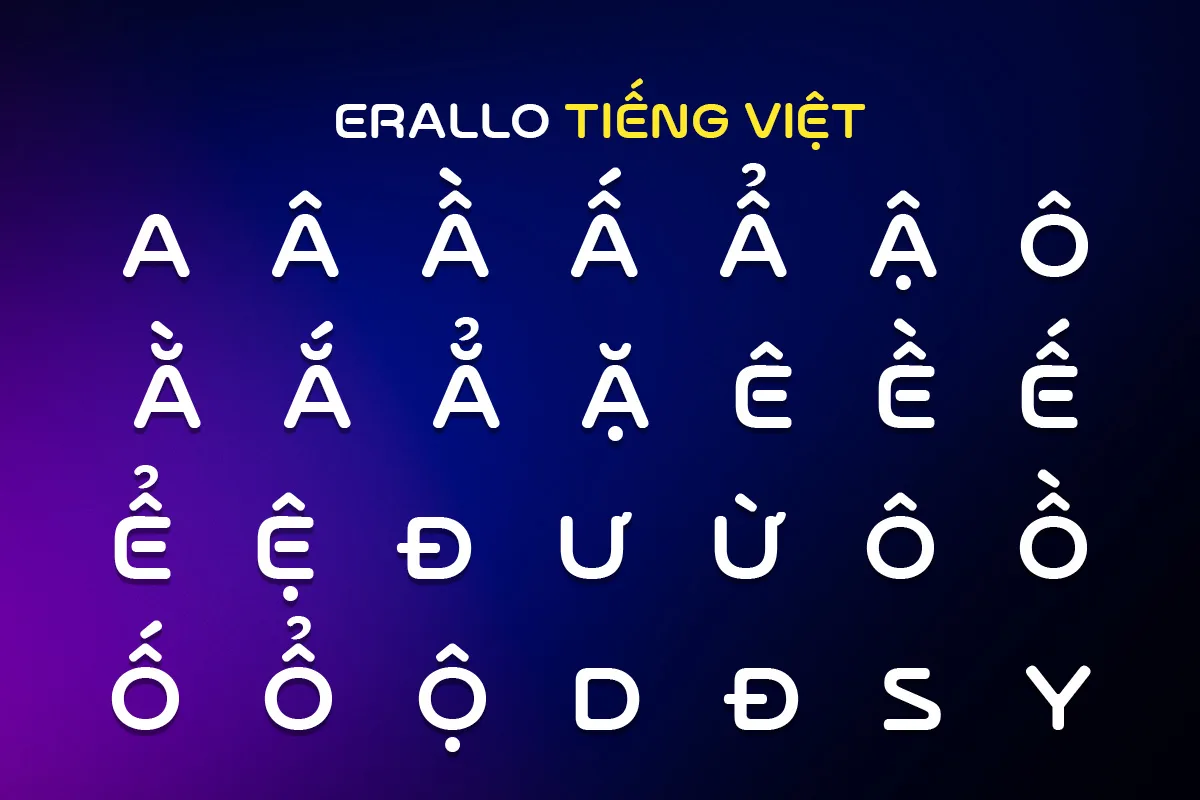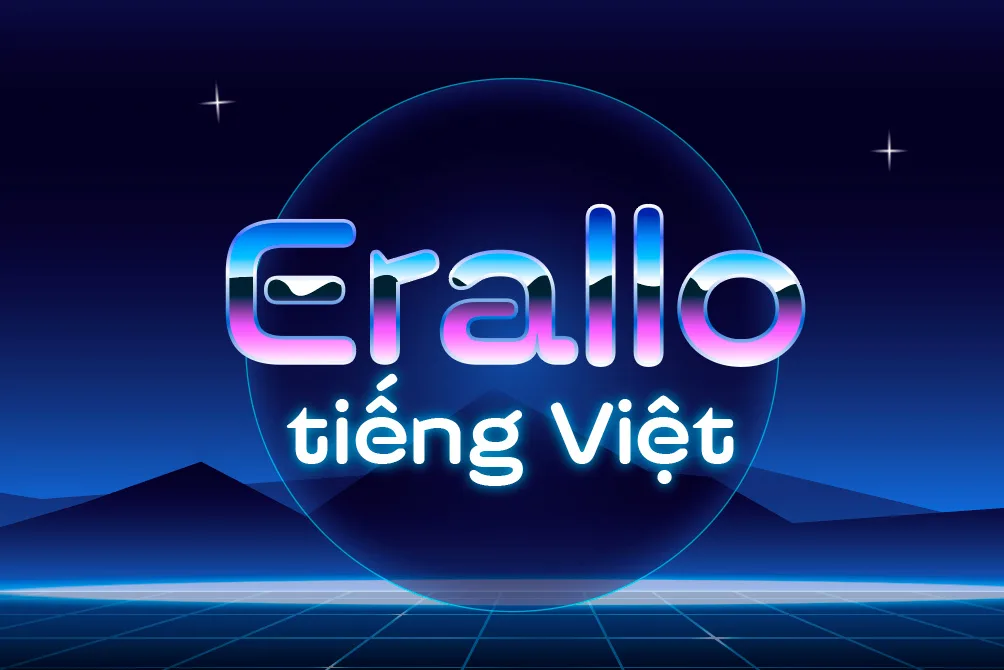
DVN Erallo tiếng Việt – Font Chữ Công Nghệ Hiện Đại Đậm Chất Tương Lai
DVN Erallo Tiếng Việt là font chữ công nghệ nổi bật với thiết kế hình học bo tròn, đường nét tối giản và phong cách futuristic đầy cuốn hút. Font mang đến cảm giác hiện đại, sáng tạo và chuyên nghiệp, đặc biệt phù hợp cho các dự án công nghệ, AI, gaming, thương hiệu số, giao diện ứng dụng và thiết kế quảng cáo cao cấp.
Với bộ ký tự tiếng Việt hoàn chỉnh cùng khả năng tạo điểm nhấn mạnh mẽ cho tiêu đề, DVN Erallo giúp thiết kế trở nên khác biệt và đậm chất tương lai. Đây là lựa chọn lý tưởng cho những ai đang tìm kiếm một kiểu chữ công nghệ độc đáo, hiện đại và bắt kịp xu hướng thiết kế mới.